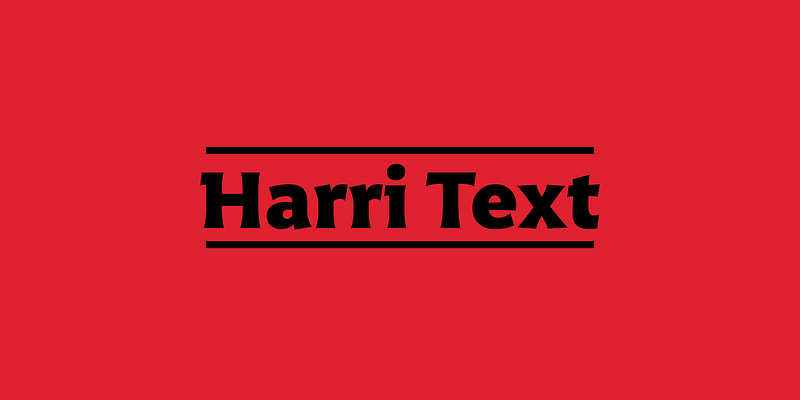
Harri Text は、Harri の拡張版以上のフォントです。2 つの書体は同じ起源、特定の風味、および多くの特異性を共有していますが、Harri はディスプレイでの使用を目的とした大文字のみの書体であり、Harri Text は新しい超軽量ウェイト、イタリック体、小文字、エディトリアル目的に適したその他の追加要素を含む真のテキストファミリーです。